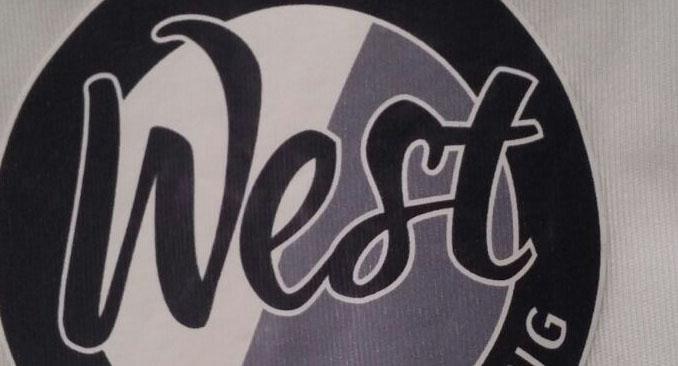
Suche gleiche oder ähnliche Schriftart
Ich bin wiedermal auf der Suche nach einer bestimmten Schriftart.
Kann mir vielleicht jemand helfen und sagen, welche Schriftart das hier ist?
Das "est" erinnert stark an die Kaushan Script — wobei nicht auszuschliessen ist, dass bei so einem Logo (?) die Kurven bearbeitet wurden. Das "W" sieht zumindest im Standardzeichenumfang der Kaushan Script anders aus.
Hallo und Danke ... Also ich denke, da es ein laie gemacht hat, dass hier keine Kurvenbearbeitung vorgenommen wurde. Das wird schon eine unbehandelte Schriftart sein. Aber vielen Dank, der Tip mit der Kaushan hilft mir erstmal ... Vielleicht hat ja noch jemand eine Idee, welche auch noch passen könnte ... Grüße!
Hallo R::bert ... Was meinst Du? ... Woher das Logo ist? ... Das stammt von einem Trikot aus unserem Verein, aber niemand kann sich an die Schriftart erinnern ... Fragen beantwortet? ... Grüße!
Oft helfen genauere Infos, woher das stammt, bei der Suche nach der Schriftart. Weil sie beispielsweise in einem pdf verwendet wurde, weil beispielsweise mehr als die gezeigten Buchstaben existieren und so weiter und so fort. "… von einem Trikot aus unserem Verein …" hilft da nur bedingt weiter, wie du dir hoffentlich vorstellen kannst.
Hej! Manchmal helfen halt Stichworte wie Firmenname (in Deinem Fall der Name des Vereins) weiter um via Google, etc. eventuell noch irgendwo (z.B. Webseite, PDF) einen Hinweis zur Schrift oder weitere Anwendungen mit mehr Zeichen zu finden. Aber meistens funktioniert das nur bei größeren Unternehmen, die schon recht professionelles Online-Marketing betreiben bzw. im Web so vertreten sind, dass Sie dabei dementsprechende Spuren hinterlassen.
Hallo ... Nee, mit solchen Infos kann ich leider nicht dienen ... Ich habe wirklich nur das Bild und mehr nicht, sorry ... Grüße!